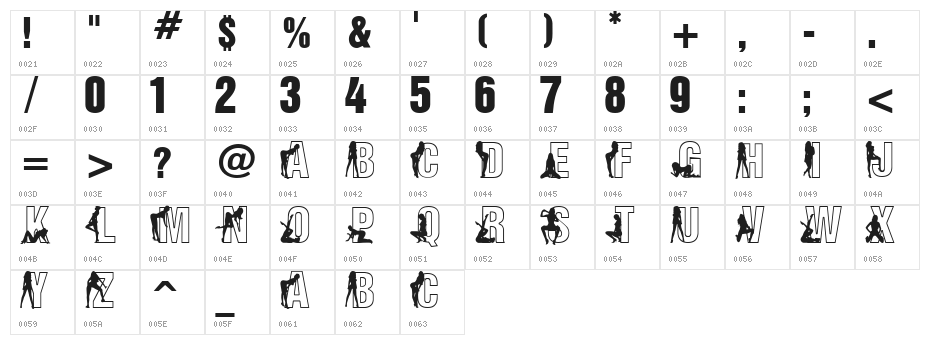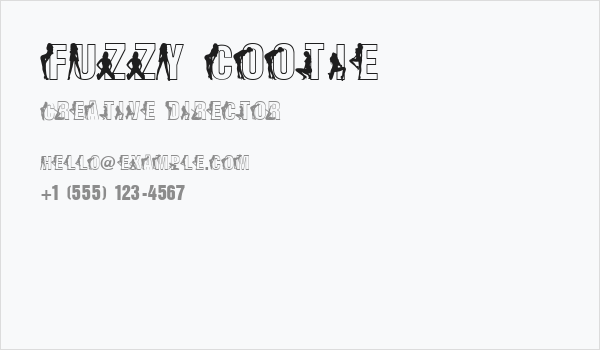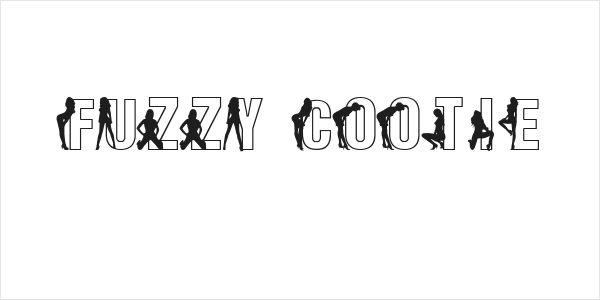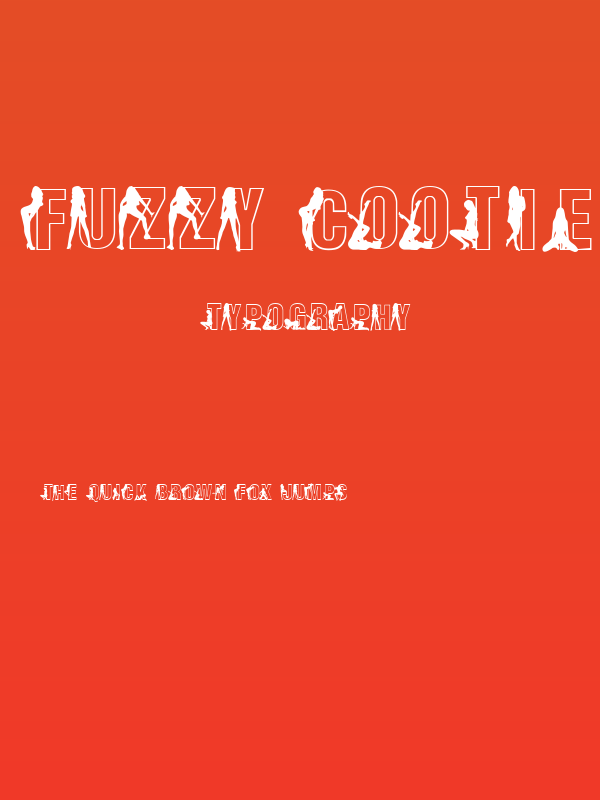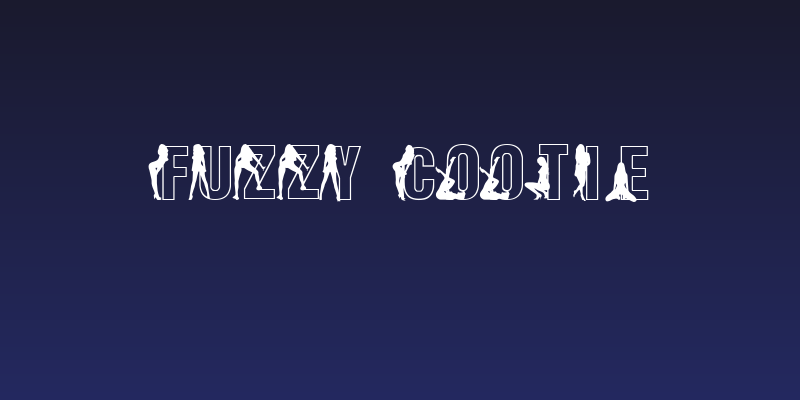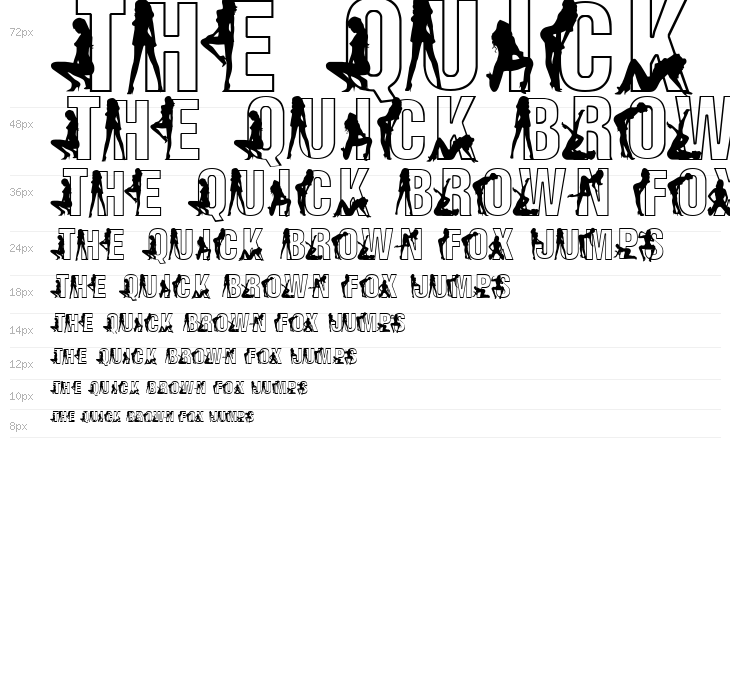
Fuzzy Cootie Font
| Vorgeschlagene Projekte | Ideal for creative projects such as posters, event flyers, or branding materials that require a fun and attention-grabbing typeface. |